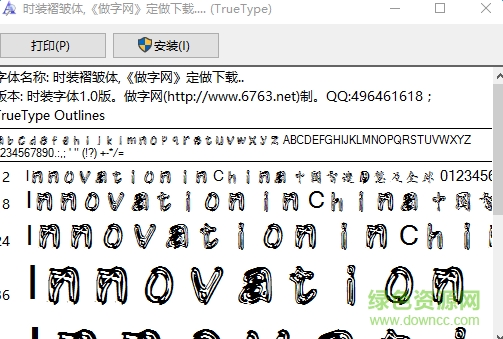
時(shí)裝褶皺體是時(shí)裝字庫(kù)中一款很有特色的電腦字體,這款字體寫出來(lái)的字就像它的名字所說(shuō)那樣是褶皺在一起的,這也是它的一個(gè)重要特點(diǎn),喜歡這款字體的朋友可以來(lái)綠色資源網(wǎng)下載。
時(shí)裝褶皺體真的是一款很不錯(cuò)的電腦字體,可以用于很多方面,不管是藝術(shù)設(shè)計(jì)還是廣告設(shè)計(jì)都是很合適的,歡迎大家來(lái)綠色資源網(wǎng)在做。